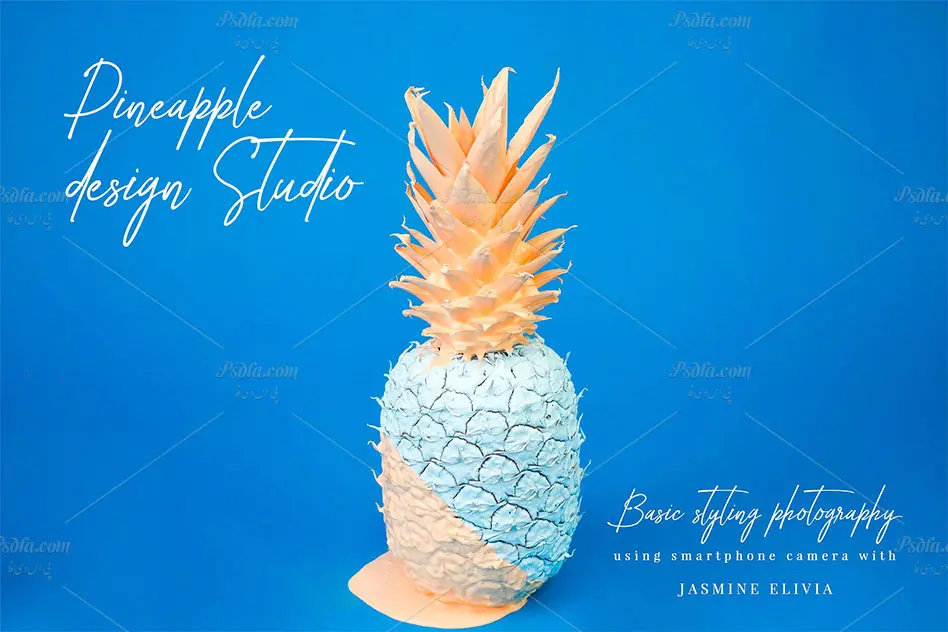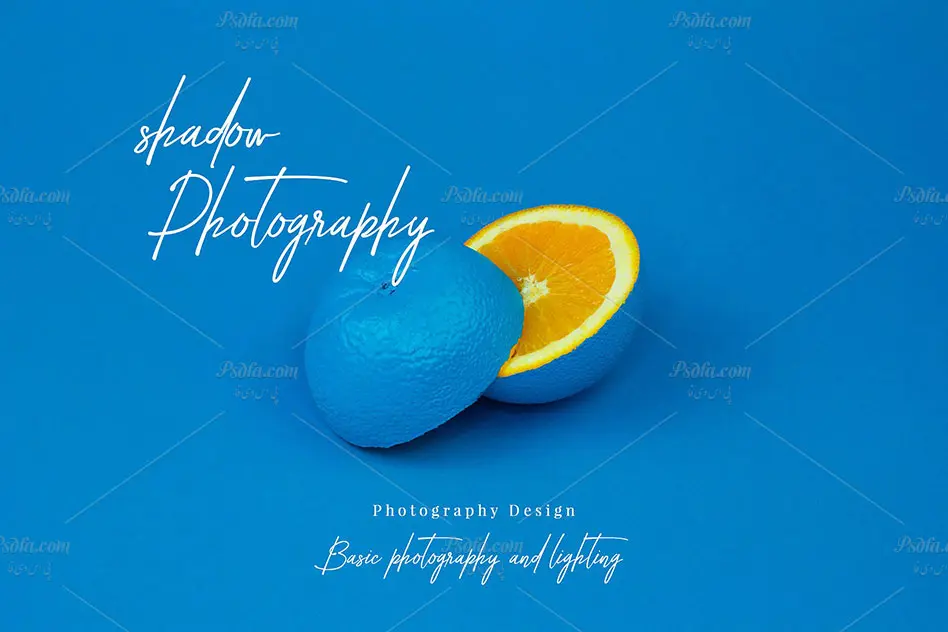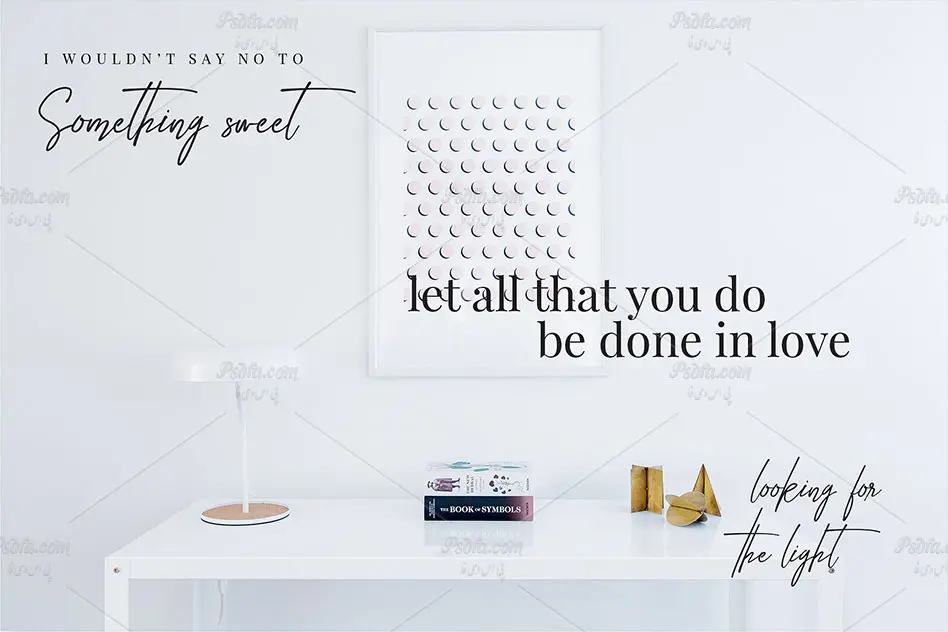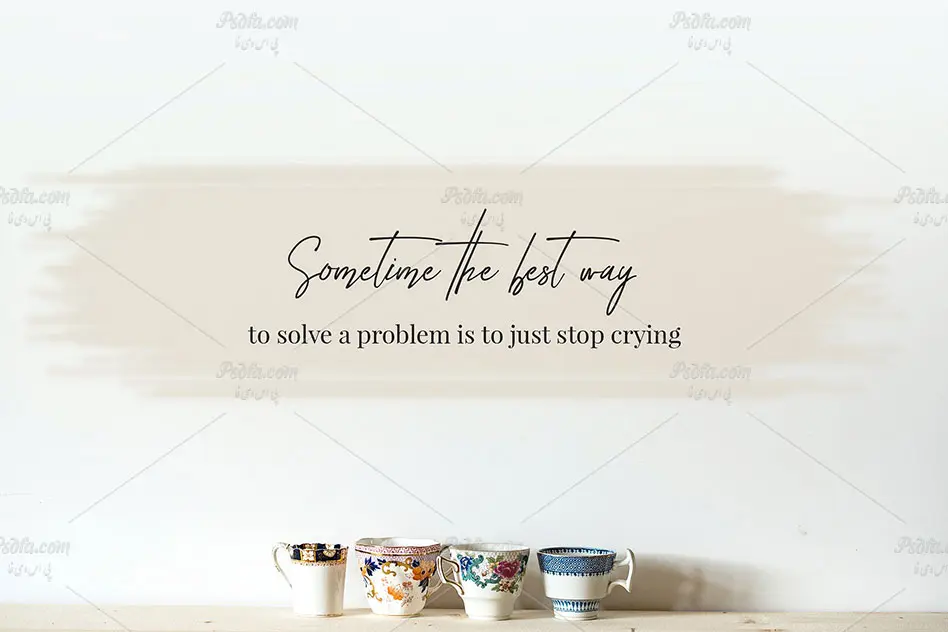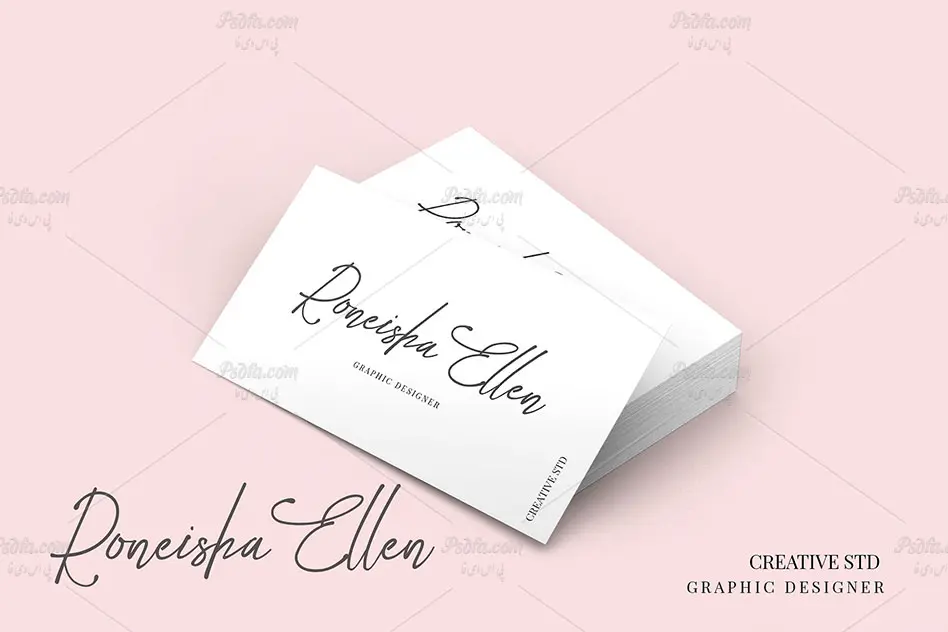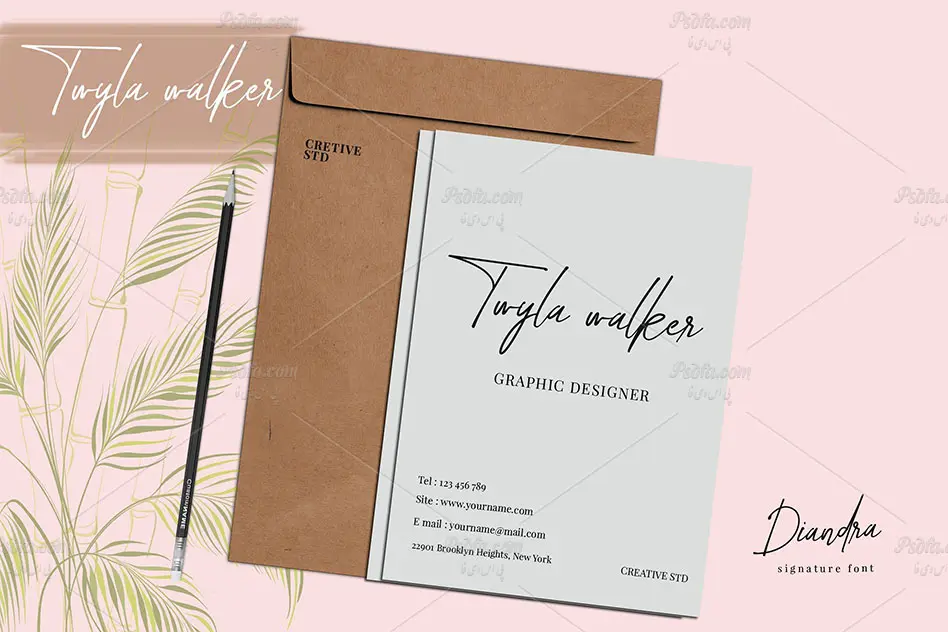
در این مطلب شاهد فونت انگلیسی فوق العاده زیبای امضاء Diandra Signature font می باشید. این فونت زیبا در قالب دو فرمت ttf و otf در سایت قرار گرفته است که با نصب هر یک از این دو فونت در پوشه فونت های سیستم خود قادر به استفاده مستقیم از آن ها در تمام نرم افزارهای گرافیکی و ویرایشگر متن از جمله نرم افزار فتوشاپ ، مجموعه نرم افزار آفیس و … می باشید. از این فونت انگلیسی می توان در طراحی انواع پروژه های گرافیکی به خصوص طراحی انواع پوستر استفاده نمود.